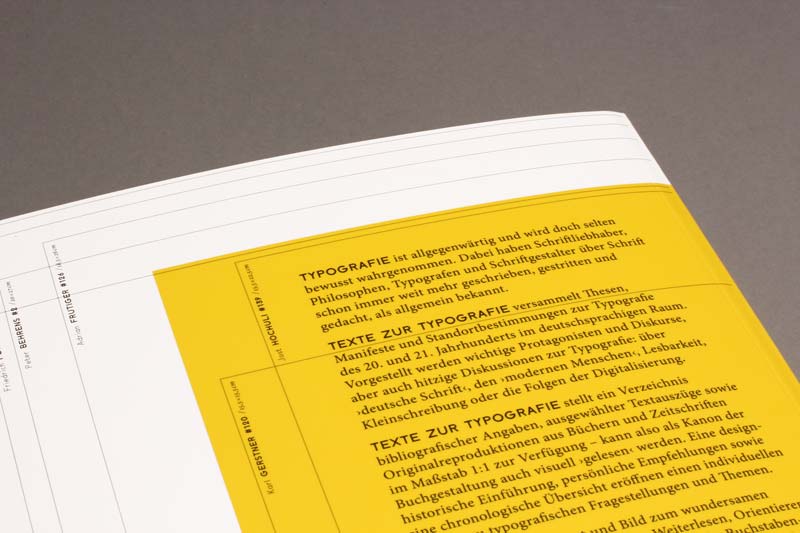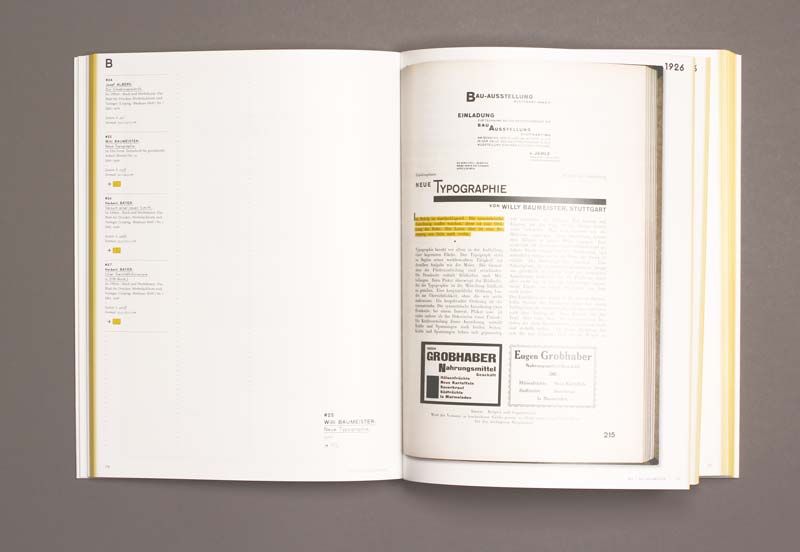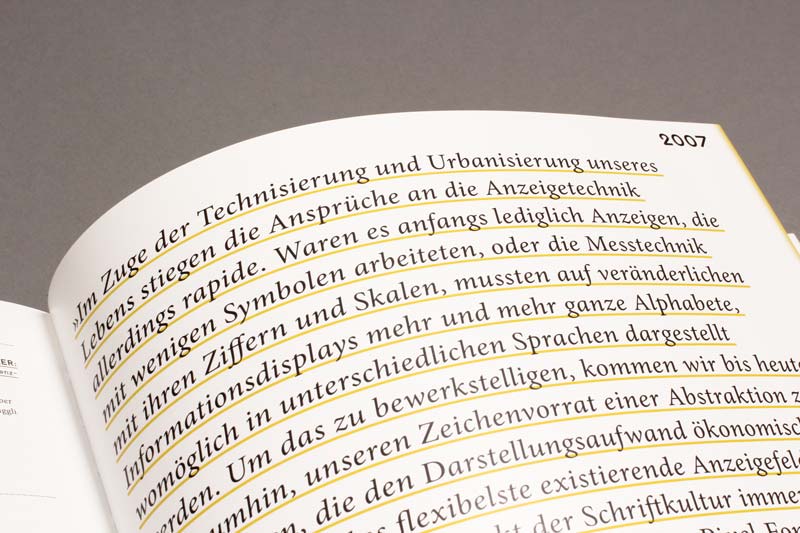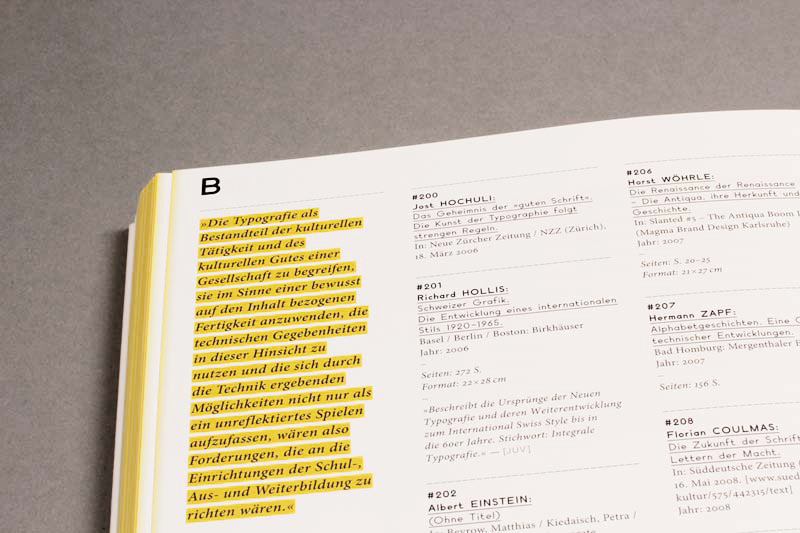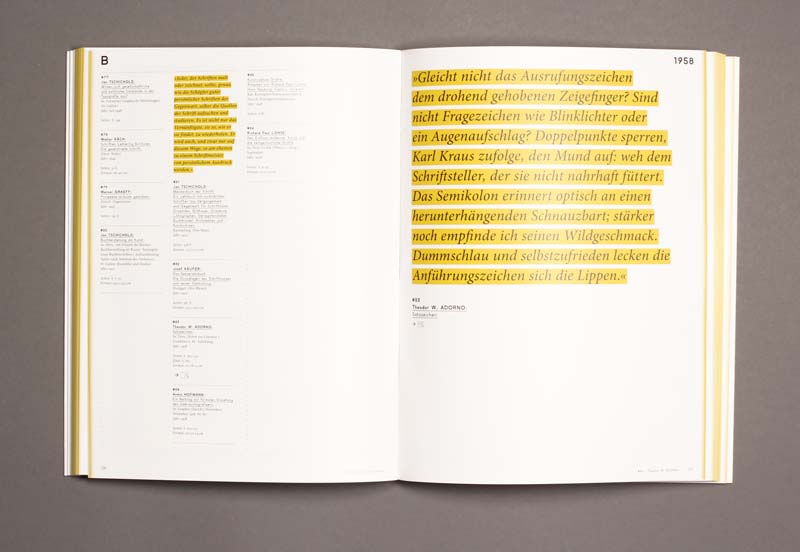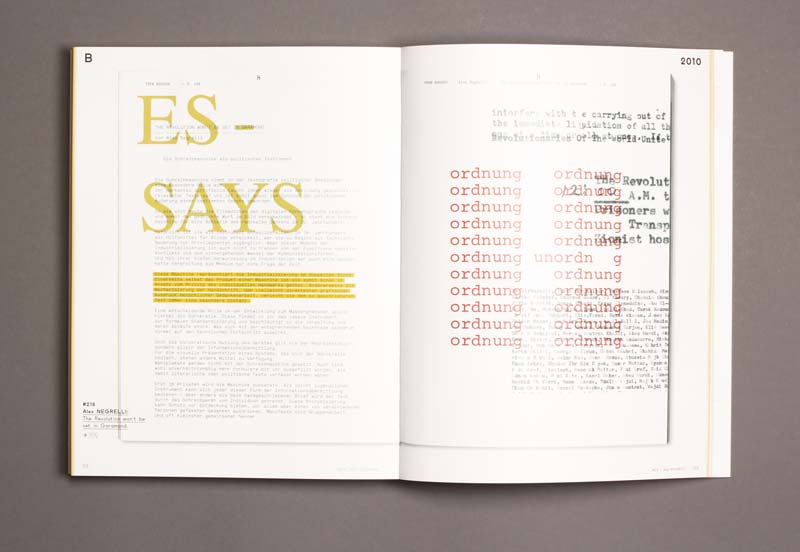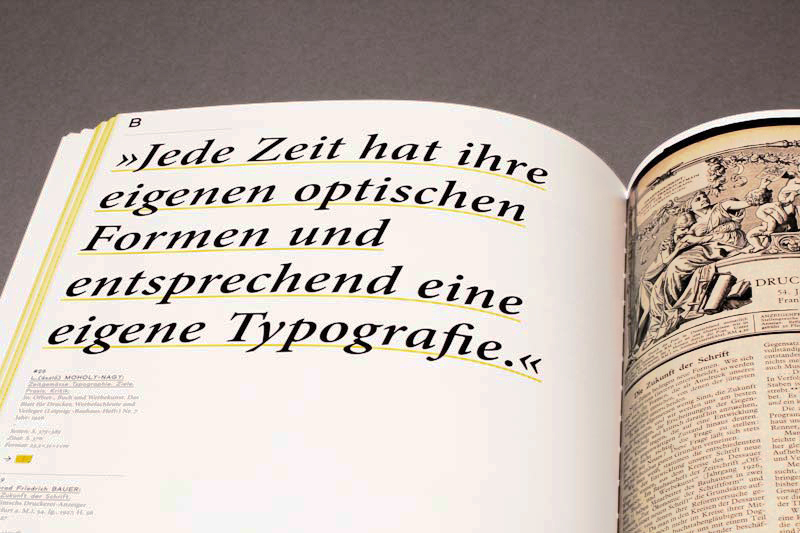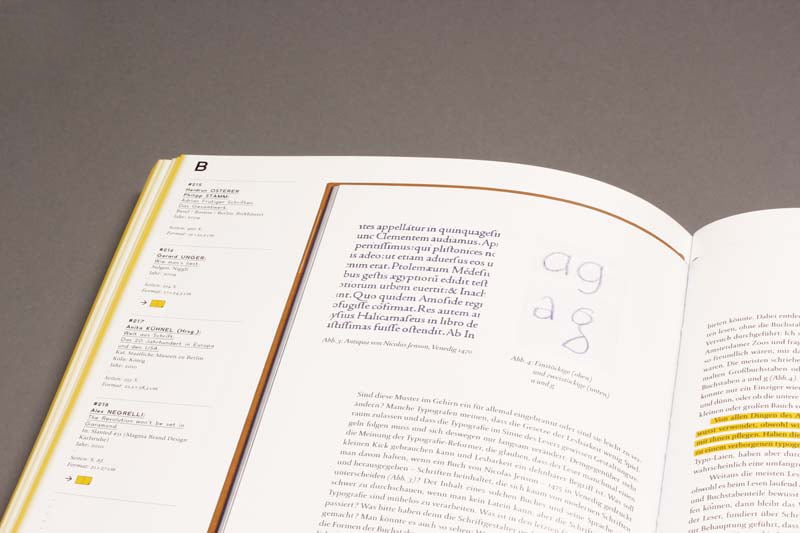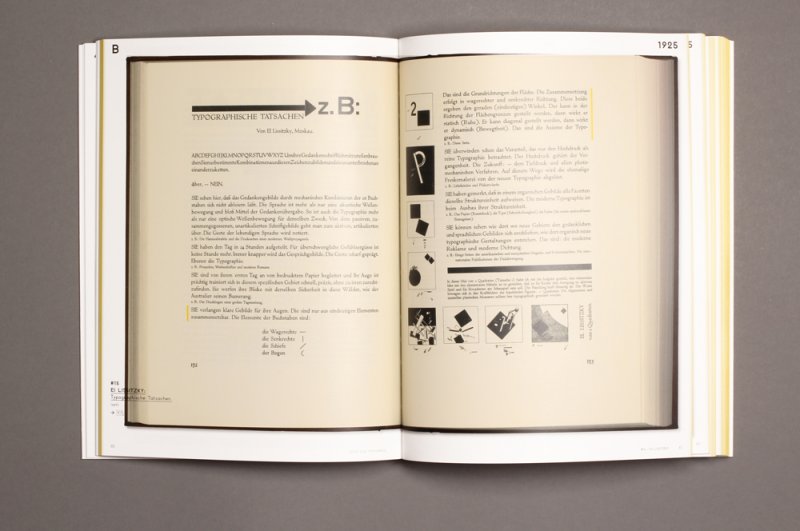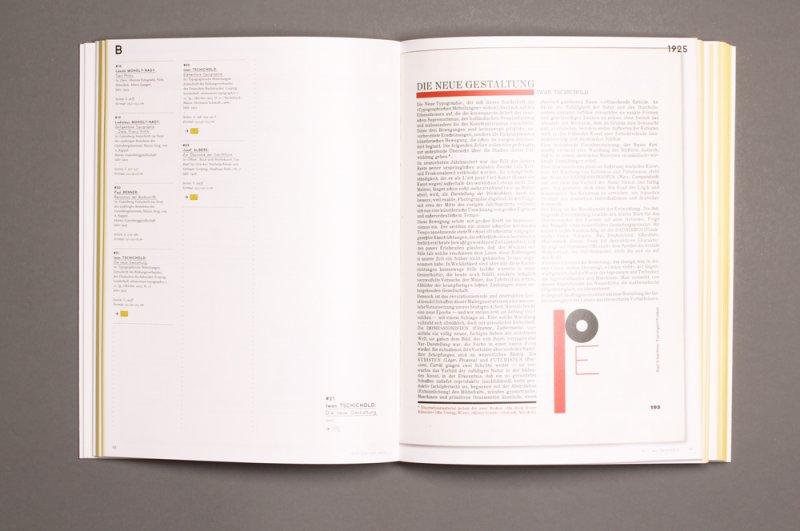
Texte zur Typografie – Positionen zur Schrift
Wir berichteten schon einmal von den ersten Blicken auf den Dummy Texte zur Typografie, den wir auf der gerade beendeten ON-TYPE-Ausstellung in Mainz begutachten konnten. Nun endlich ist das Buch, herausgegeben von Petra Eisele und Isabel Naegele, im Niggli Verlag veröffentlicht worden.
Aus dem Pressetext: Typografie ist allgegenwärtig und wird doch selten bewusst wahrgenommen. Dabei haben Schriftliebhaber, Philosophen, Typografen und Schriftgestalter schon immer über Schrift weit mehr geschrieben, gestritten und gedacht, als allgemein bekannt. Texte zur Typografie versammelt Thesen, Manifeste und Standortbestimmungen zur Typografie des 20. und 21. Jahrhunderts im deutschsprachigen Raum. Vorgestellt werden wichtige Protagonisten und Diskurse, aber auch hitzige Diskussionen zur Typografie: über deutsche Schrift, den modernen Menschen, Lesbarkeit, Kleinschreibung oder die Folgen der Digitalisierung. Texte zur Typografie stellt ein Verzeichnis bibliografischer Angaben, ausgewählter Textauszüge sowie Originalreproduktionen aus Büchern und Zeitschriften im Maßstab 1:1 zur Verfügung – kann also als Kanon der Buchgestaltung auch visuell gelesen werden.
Eine designhistorische Einführung, persönliche Empfehlungen sowie eine chronologische Übersicht eröffnen einen individuellen Zugang zu typografischen Fragestellungen und Themen. Eine Sammlung in Wort und Bild zum wundersamen Kosmos der Schriftzeichen. Zum Weiterlesen, Orientieren und Streiten. Für Besserwisser, Bibliophile, Blogger, Buchstabensammler, Designkritiker, Lehrende, Germanisten, Gestalter, Kunsthistoriker, Pädagogen, Schriftliebhaber, Studierende, Leser, Theoretiker, Typo-Laien und Typo-Nerds.
Texte zur Typografie Positionen zur Schrift
Herausgeber: Petra Eisele, Isabel Naegele